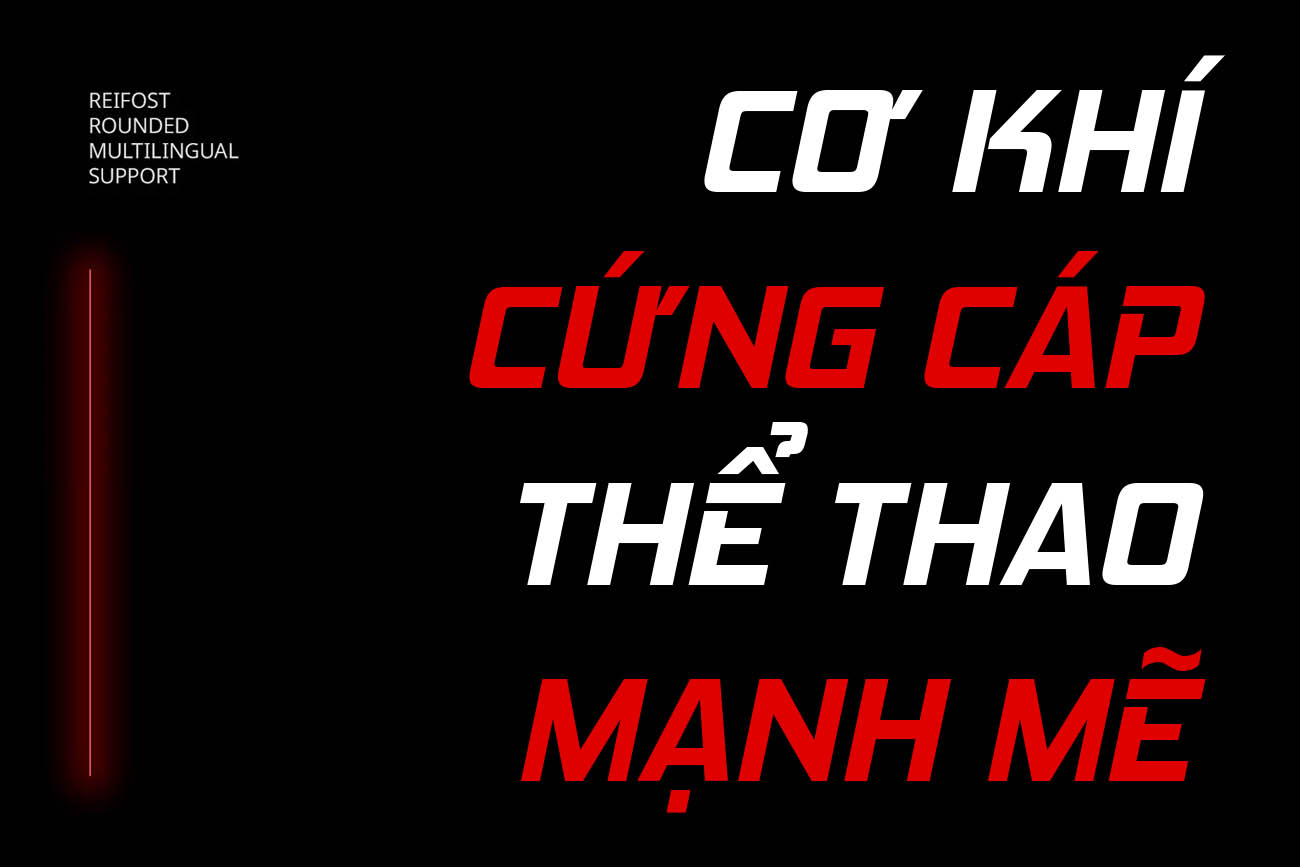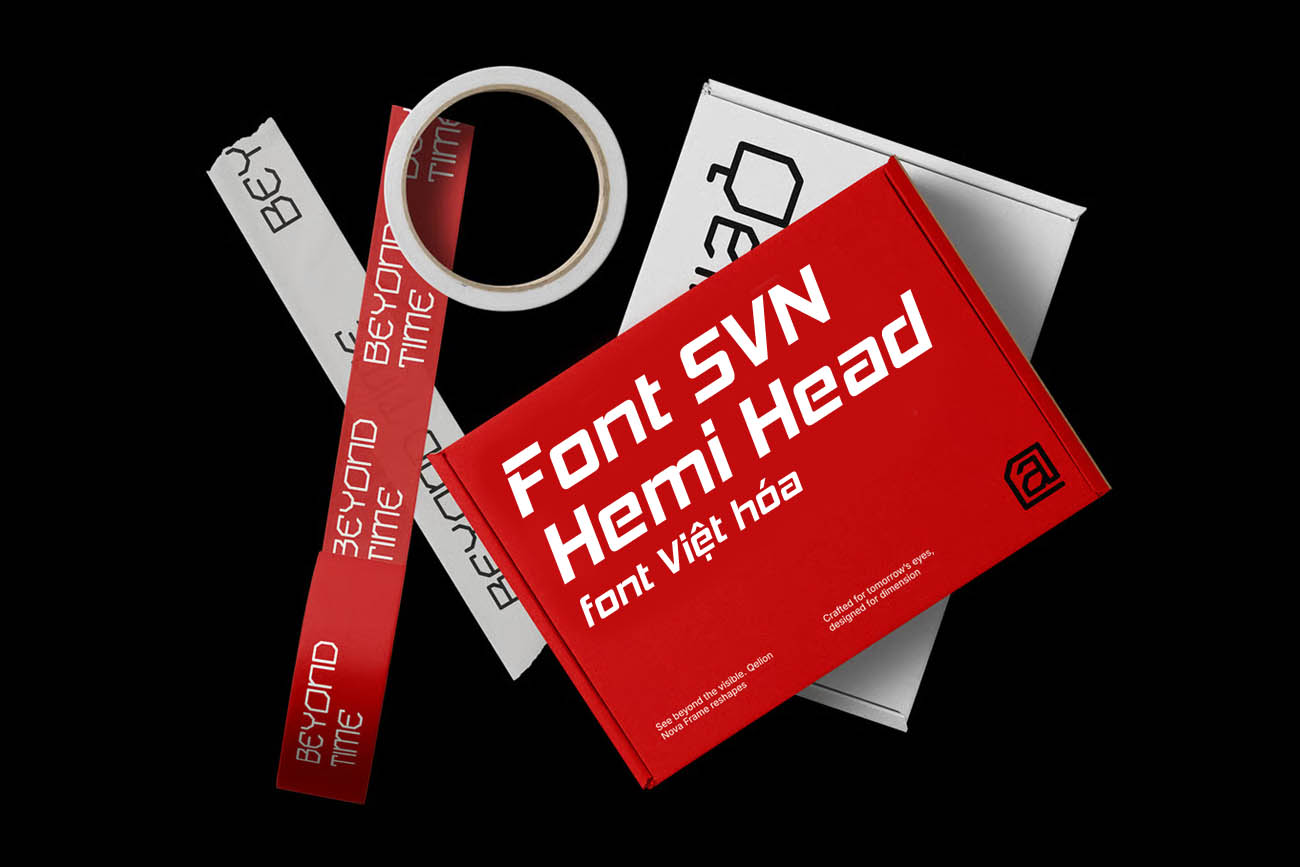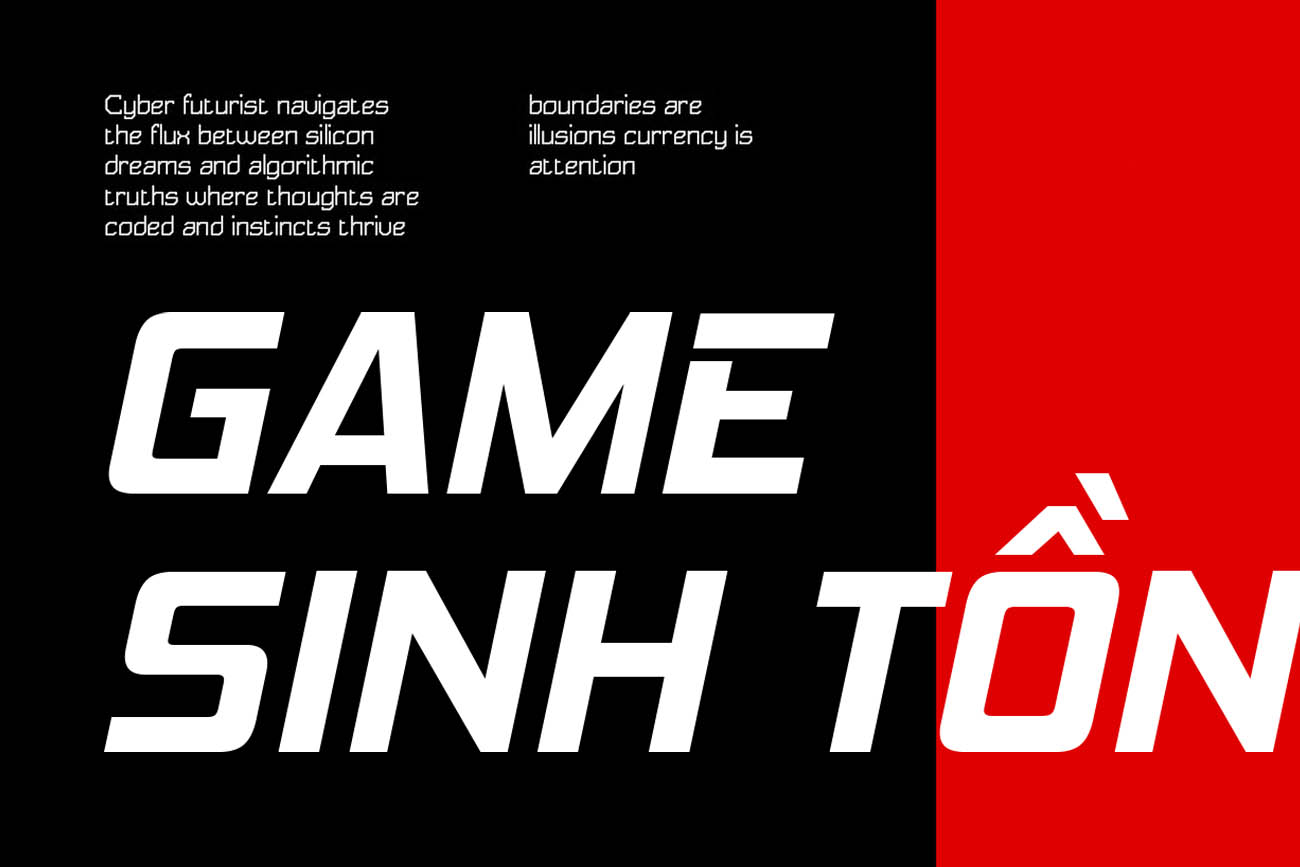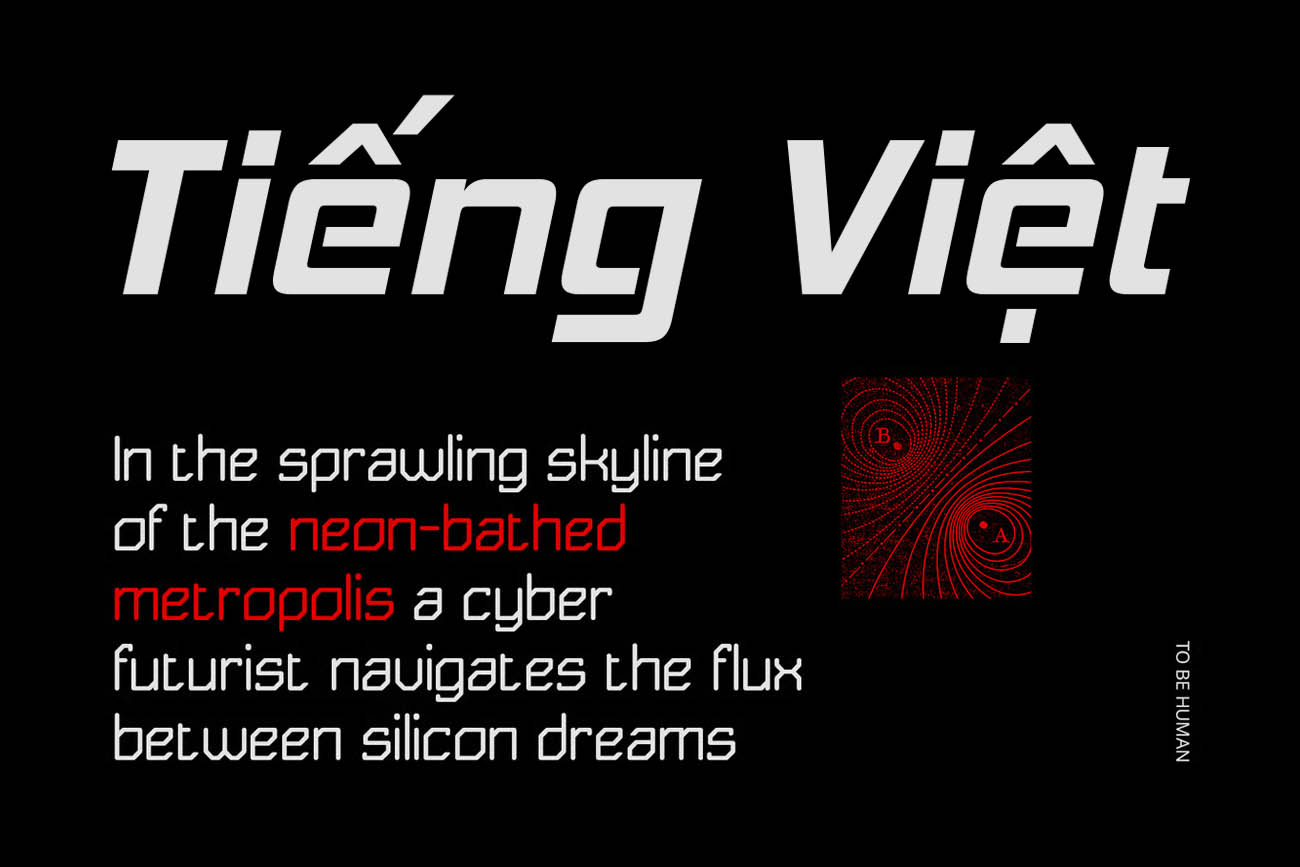
Tác giả Ray Larabie
Việt hóa Team SVN
Bạn đang tìm kiếm một font chữ thể thao Việt hóa mang phong cách mạnh mẽ, tốc độ và hiện đại? Font SVN Hemi Head chính là sự lựa chọn hoàn hảo cho các thiết kế game, giải đấu thể thao, eSport hoặc banner mang tính hành động cao.
Giới thiệu về font SVN Hemi Head
SVN Hemi Head là bản Việt hóa từ font gốc Hemi Head do Ray Larabie nhà thiết kế nổi tiếng sáng lập Typodermic Fonts phát triển. SVN Hemi Head là một kiểu chữ không chân nổi bật với các đường nét vuông vức, sắc cạnh và khỏe khoắn. Font được thiết kế lấy cảm hứng từ các logo xe đua, mô tô, và công nghệ tốc độ cao. Nhờ đó, Hemi Head mang đến cảm giác tăng tốc, quyết đoán và nam tính, rất phù hợp cho các dự án thiết kế cần sự bứt phá và năng lượng.
Mô tả tổng thể đường nét
Font SVN Hemi Head sở hữu đường nét vuông vức, cứng cáp và dứt khoát, tạo cảm giác chắc chắn và mạnh mẽ ngay từ cái nhìn đầu tiên. Các nét chữ được thiết kế với độ nghiêng nhẹ, mang đến hiệu ứng chuyển động và tốc độ – rất phù hợp với các chủ đề về thể thao, cơ khí hoặc game hành động. Kiểu dáng không chân (sans-serif), kết hợp với các góc bo gãy gọn và hướng xiên về phía trước, giúp font mang đậm tinh thần công nghiệp – hiện đại – nam tính. Tổng thể font tạo ra một ấn tượng thị giác mạnh, dễ đọc, nổi bật khi dùng cho tiêu đề, poster hoặc logo mang tính năng động.
Việt hóa chỉn chu, hỗ trợ tiếng Việt đầy đủ
Phiên bản Việt hóa được thực hiện bởi Team SVN Fonts, đảm bảo hỗ trợ đầy đủ dấu tiếng Việt, chuẩn Unicode và không lỗi ký tự. Bạn có thể sử dụng font này thoải mái trong các thiết kế tiếng Việt mà không cần chỉnh sửa lại các chữ dấu như “ă, â, ê, đ…”
Lý tưởng cho thiết kế game, eSport và thể thao
• Poster game, giải đấu thể thao
• Banner thương hiệu eSport, công nghệ
• Logo và thiết kế cơ khí, kỹ thuật
• Typography mang phong cách sport, digital, mạnh mẽ
Nếu bạn đang tìm một font chữ Việt hóa cho thiết kế game hoặc font chữ thể thao mạnh mẽ, hiện đại, thì SVN Hemi Head chắc chắn là một lựa chọn đáng giá.